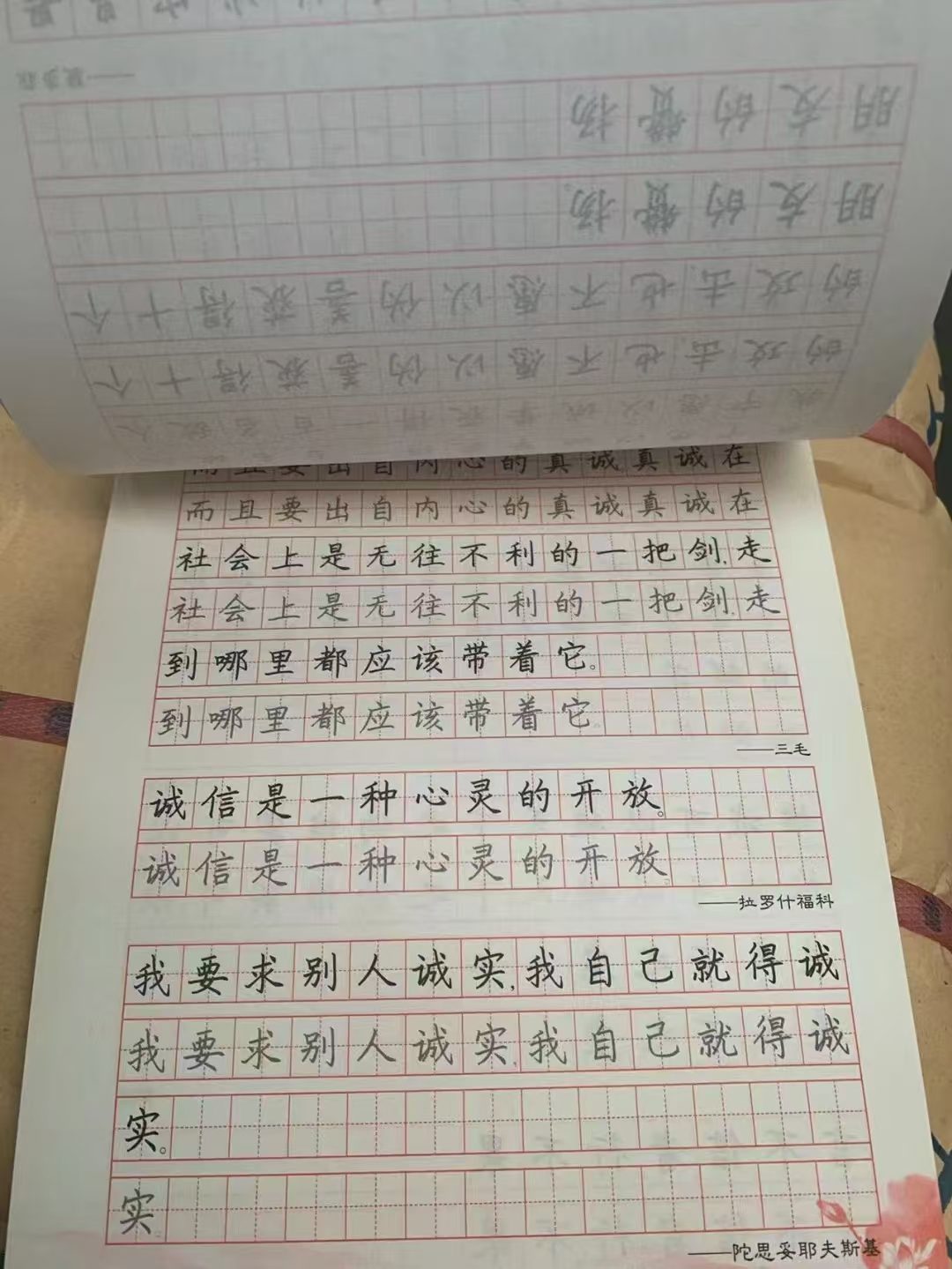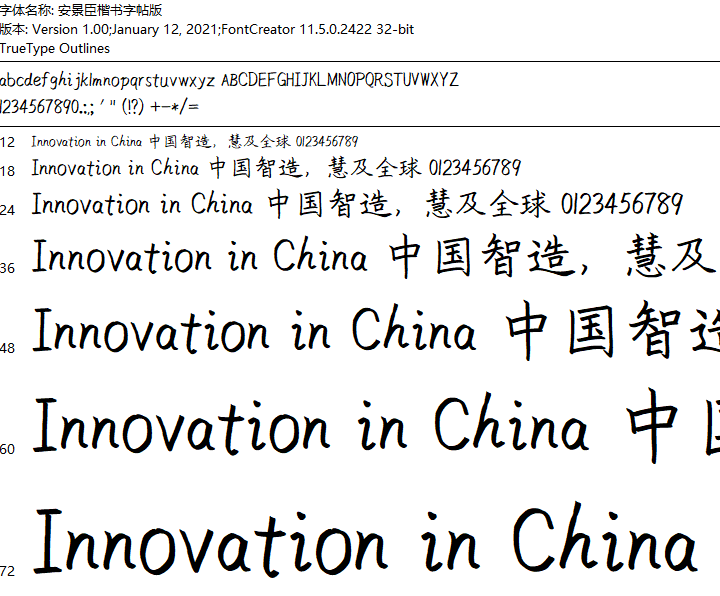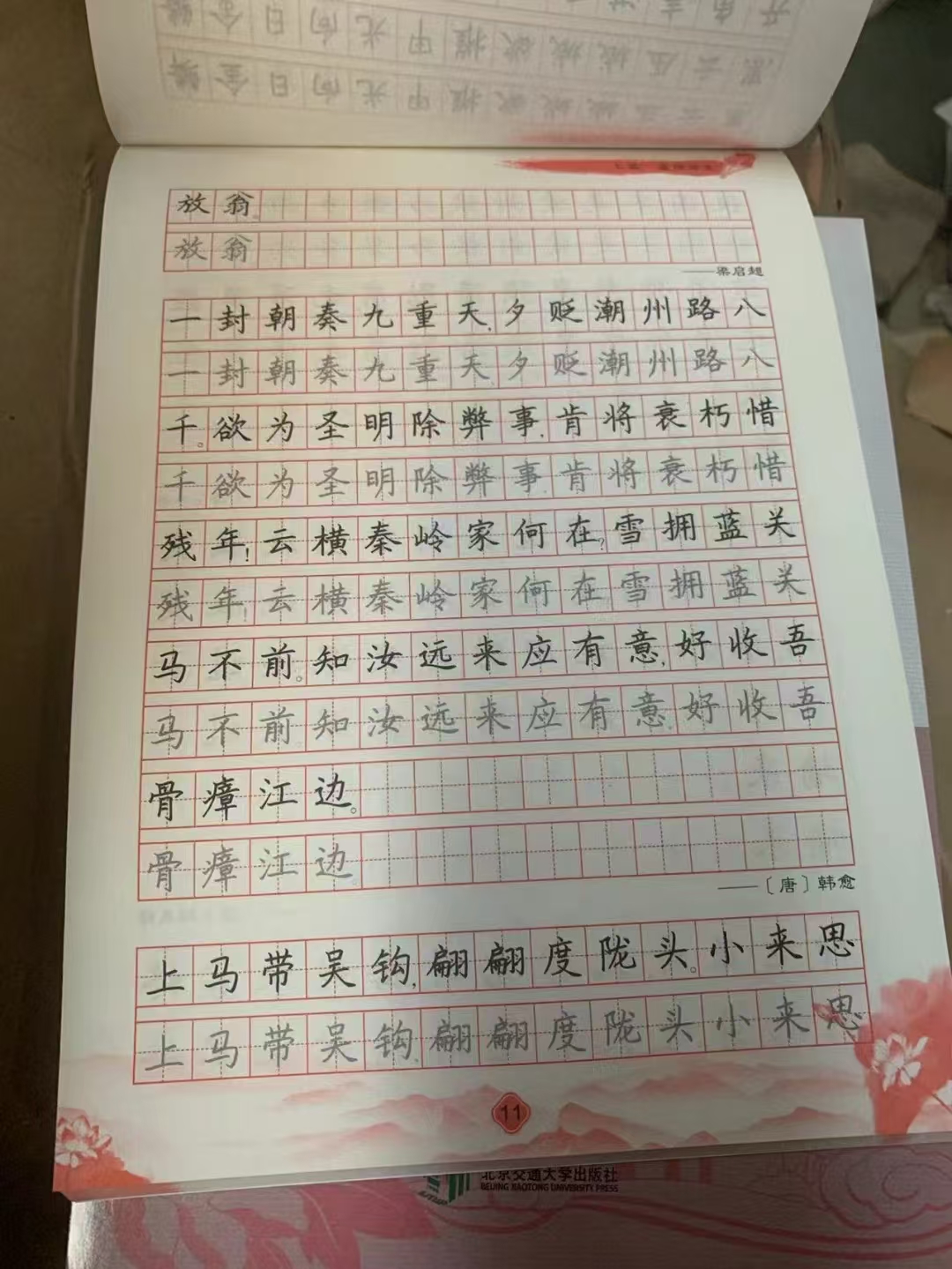
安景臣硬笔楷书字体
风格:手写体
语系:中文-简体
字数:GB2312(6763字)
类型:楷体
安景臣硬笔楷书字体
描述:一款可以做字帖的字库。并不是所有的字库都能做字帖!要想做字体帖,一款好的字体是必不可少的。首先字体要标准,还要符合书写规范,不能有丝毫差错,否则就是误人子弟!为了吸引人,字体还要有个性,有时尚感!本款字体采用现代硬笔书写,时尚感、新鲜感十足,深受广大学生喜爱,曾作为正规出版字帖选用字库,全国发行。